提及“一夜暴富”这个词,大家难以把它跟书法艺术想到在一起。一般而言,书法艺术应该是跟“修身养性”、“恬淡”等关键字联络在一起。可是,就在一位街边乞讨者的身上,将书法艺术跟发大财取得成功地联络在一起。
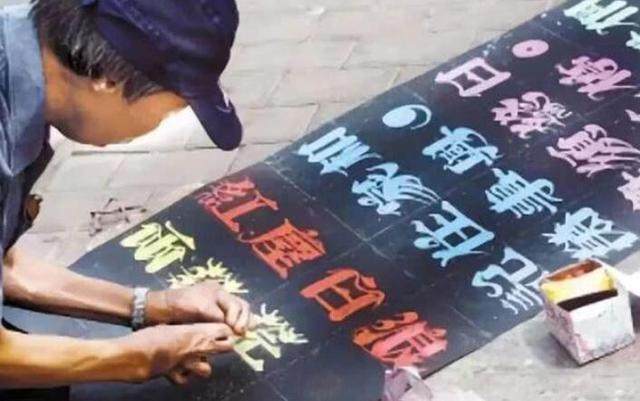
他原本是一个乞讨者,并且是一个身带残废的乞讨者,可是他却沒有向运势妥协,只是勤学苦练十年书法艺术,练出了一手好看的铅笔印刷体,还被方正字库回收了,而且方正字库申明:中文字库50年收益归他全部!这个人便是崔显仁,之前是一个在街上靠书写谋生的乞讨者,可是如今的他不但并不是乞讨者了,并且還是一个富人了,由于他的粉笔字被方正字库看好了,方正字库准备将他的字收益中文字库!
方正字库出文称:烟台市这名奇人异事一手好看的粉笔字,深深打动了大家!真心实意期待能够 和他协作,将老年人那漂亮伸展、隽秀大气的字体样式搜罗到方正字库。大家一起来寻找这名老年人吧!”
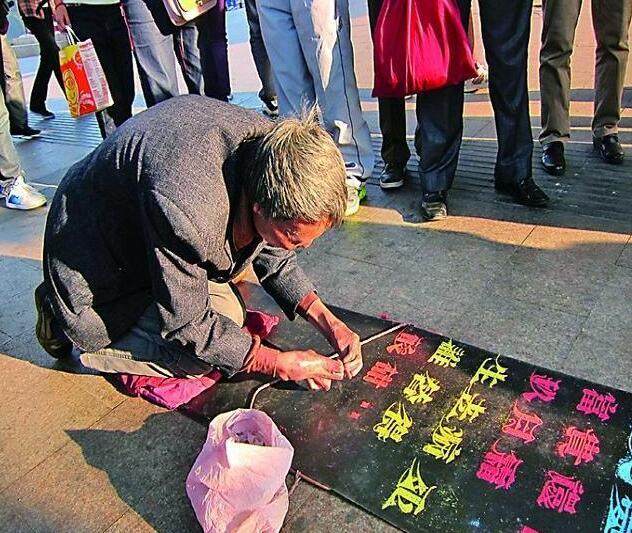
历经一番勤奋,华康责任人最后看到了崔显仁。随后将崔显仁的“七色彩虹体”书法艺术百度收录到方正字库里,而且将这种字体发售,以该字体样式将来50年的收益付款给崔显仁,以表示感激。还将这种字体取名为“显仁字体样式”。
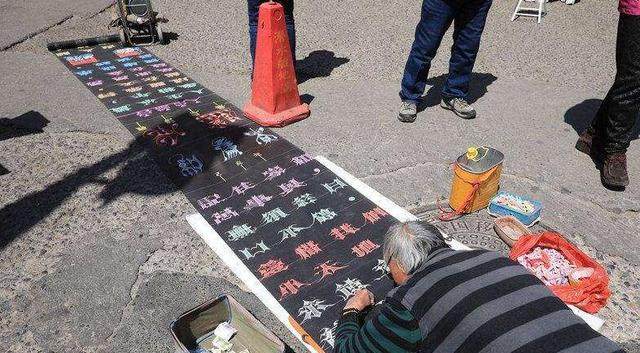
仅有中小学3年级文化艺术的崔显仁变成中国当选“方正字库”的一位“街头艺人”,也是一位靠书法艺术进行人生道路逆转,从一名靠铅笔书法艺术乞丐到借助字体样式稿酬赚钱的经典励志大咖。